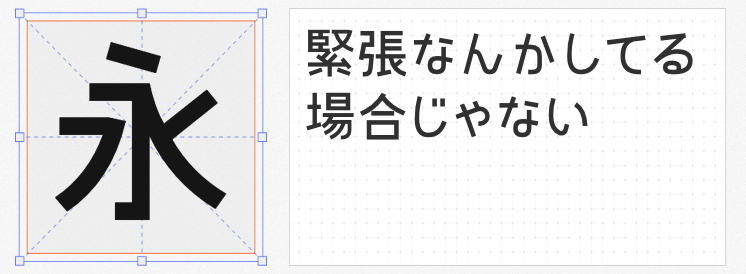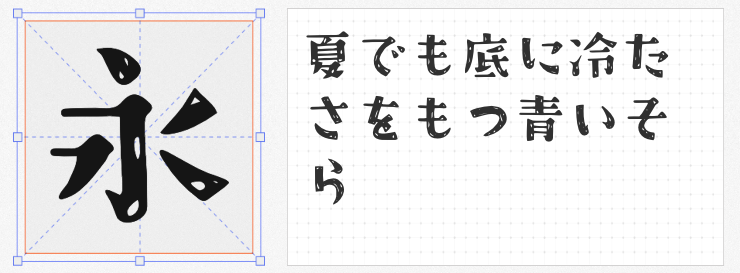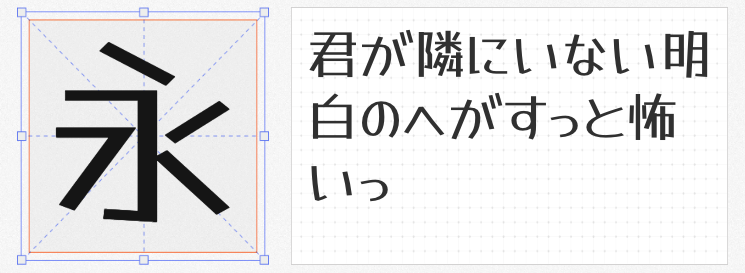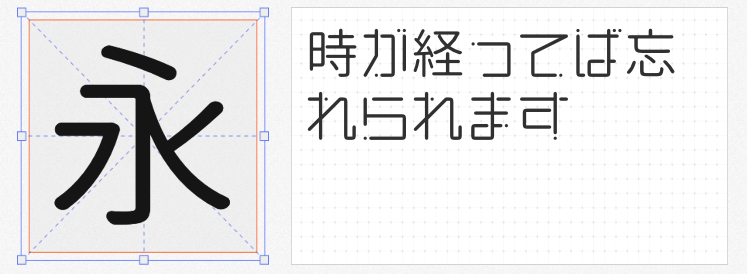
在设计的广阔天地里,字体是传递情感与风格的重要媒介。对于追求独特与创意的设计师而言,选择合适的日文字体能为作品增添一抹别样的风情。今天,就为大家推荐四款既免费商用又充满创意的日文字体,让你的设计作品焕发新生。
1. 小夏
这款字体以其简约而不失格调的设计脱颖而出。线条简洁流畅,视觉效果干净利落,非常适合追求极简风格的设计项目。无论是作为标题还是正文,小夏都能以其独特的清新感,为作品带来一丝宁静与雅致。
2. 恋星圆体α
灵感源自热门漫画/动画《恋爱小行星》的logo,这款字体将直线与圆润完美融合。下边缘与上边框巧妙对齐,既保留了直线的稳重,又不失圆润的亲和力。更令人惊喜的是,它还特别收录了表示小行星的天文符号,为天文、科幻主题的设计增添了无限可能。
想要为设计注入一抹手绘的温馨与可爱?Tanugo手写体 Regular绝对是你的不二之选。它模仿了马克笔手绘的效果,既保持了手写的亲切感,又确保了阅读的流畅性。无论是儿童书籍、卡通插画还是创意海报,Tanugo都能以其独特的可爱气质,赢得观众的喜爱。
4. クラフト明朝
这款字体以其手绘的哑光质感独树一帜。在传统明朝体的基础上,クラフト明朝融入了手绘的元素,使得每一笔每一划都透露出匠人的用心与温度。它既保留了明朝体的端庄与典雅,又增添了几分手绘的随性与创意,非常适合用于追求独特质感的设计项目。
这四款免费商用的日文字体,每一款都蕴含着无限的设计潜力。不妨在下次创作中大胆尝试,让它们成为你灵感碰撞的火花,共同打造出令人眼前一亮的作品吧!